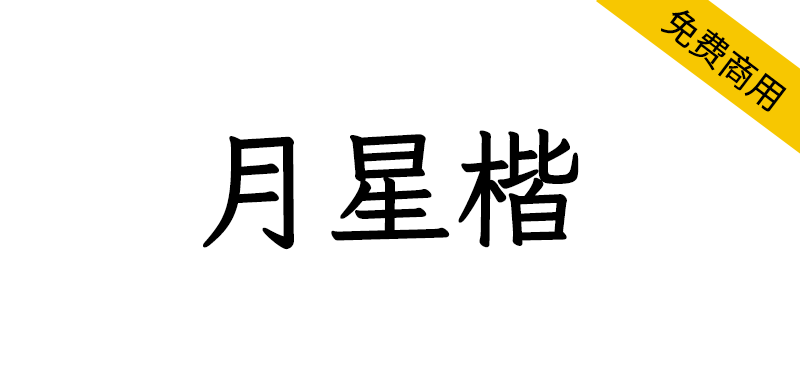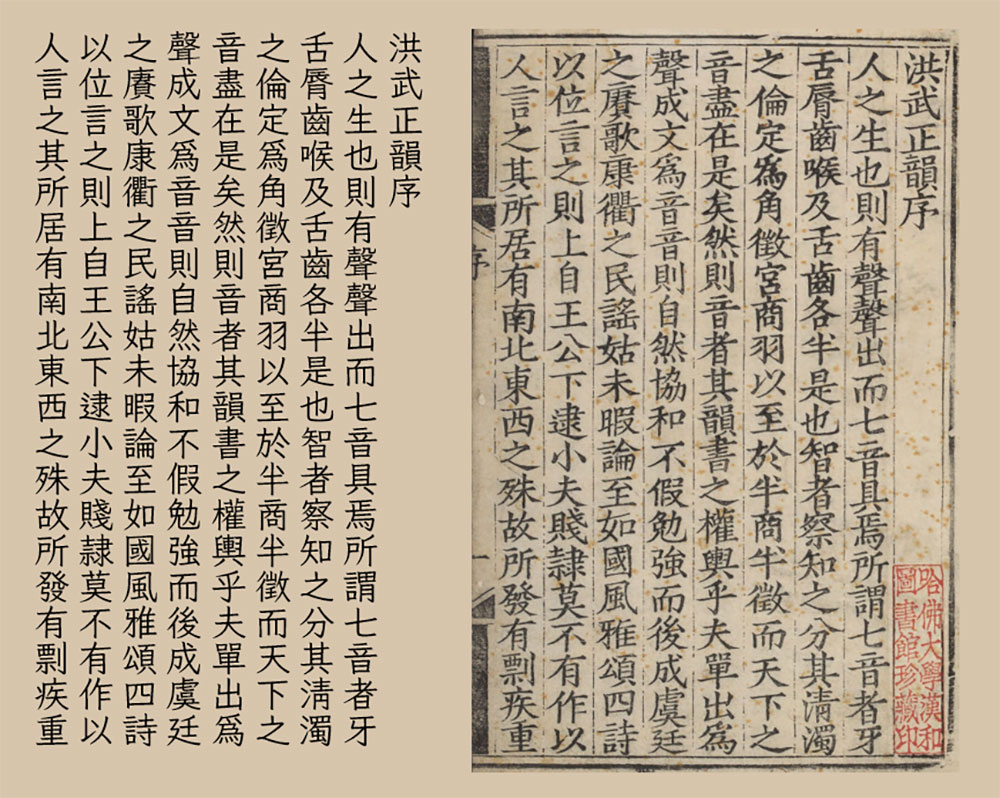
月星楷(Moon Stars Kai)是一款由 Klee 衍生旧字形或古体字形风格的中文字体。在 Klee One 的基础上,结合霞鹜文楷 TC、霞鹜文楷以及芫荽字形,参照《洪武正韵》(明嘉靖四十年刘以节刊本)制作。部分字形在现代书写中已经很少见,但可常见于书法字贴。
月星楷 繁(Moon Stars Kai T):由月星楷修改,简入繁出的字体。此字体使用了 OpenType 功能,可根据文本内容动态匹配一简多繁的情况。